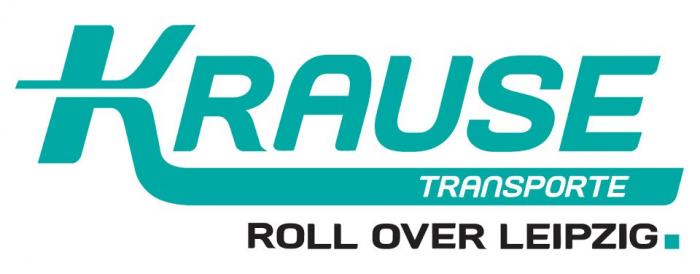
Suche Schriftart von Krause Transport Leipzig
Auch das RAUSE sieht mit nicht nach einem Font aus, sondern gebastelt, um nicht zu sagen verbastelt. Falls überhaupt Font, dann wohl eher ein Freefont.
Das ist zumindest die selbe Schrift wie die Unterzeile, eben nur kursiv. Liegt in deren pdf auch nur als Vektoren drin, nicht als Schrift …
Sieht aus wie ein Mashup aus Arial und Bank Gothic. Wenn die Schrift sonst nirgendwo so auftaucht kann es auch komplett gebastelt sein.